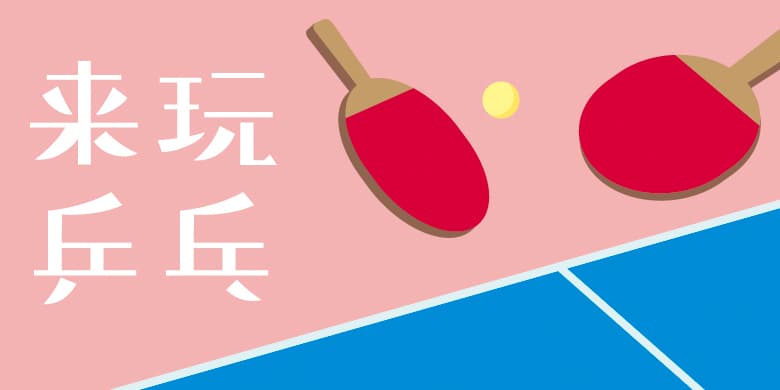
2020年方正推出与日本合作的一款字体。这款字能宽松的氛围中体现出天真烂漫的可爱。汉字和假名不同大小的凸凹感在排版时能表现出一种节奏感,其轻快提起的点提撇捺这些特征能让标题和广告语更加生动活泼。
ゆるい雰囲気にあどけない愛らしさを醸し出す書体です。漢字と仮名で異なるサイズの凸凹感が、文字を組んだ際にリズミカルな表現になります。軽やかに跳ねたテンとハライの特徴はタイトルやキャッチコピーを活き活きとさせます。